В 2011 году была переведена хорошая статья „Лучшие шрифты для программирования“. Теперь представляется список самых удачных шрифтов для кода на момент июня 2014 года.
Хотя я и уверен, что многих устраивает Courier New, используемый по умолчанию в Windows во многих редакторах. Но, как человек любящий типографику, настаиваю обратить внимание на одну из гарнитур из этой статьи. Хороший шрифт — это прекрасно!
Шрифты гарнитур будут оцениваться по качеству кириллицы и красоте всех остальных символов, применяемых во время написания кода. Для демонстрации использовался редактор Brackets. Важно, изображения в статье не могут отражать реальные ощущения от применения шрифта в вашем редакторе. Поэтому лучше попробовать несколько вариантов и выбрать подходящий.
PT Mono
Разработан в России при поддержке Федерального агентства по печати и массовым коммуникациям РФ. На сайте разработчиков можно найти более подробное описание.
Обладает очень качественной кириллицей. Но в остальном имеет много недостатков. Символ «минус» ниже символа «плюс», и не оцентрован относительно знака «равно», т. е. «-=» будет смотреться не красиво. Все скобки располагаются слишком низко, что тоже будет не удобно.
Эти шрифты плохо подходят для программирования, но могут понравиться верстальщикам.
Нормальное начертание
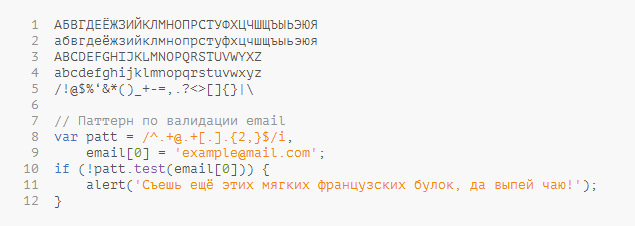
Более темное начертание
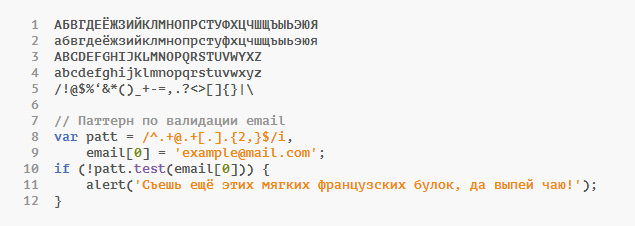
Droid Sans Mono
Семейство Droid разработано корпорацией добра для мобильных устройств. Доступен в Google Fonts, но эта версия имеет существенный недостаток — неперечеркнутый ноль. Версию с перечеркнутым, а также нулем с точкой, можно скачать на стороннем сайте.
Отличается довольно сносной кириллицей. Хорошо подходит для любого кода. Я уже несколько лет использую именно его. Но шрифт всё же имеет небольшие недостатки.
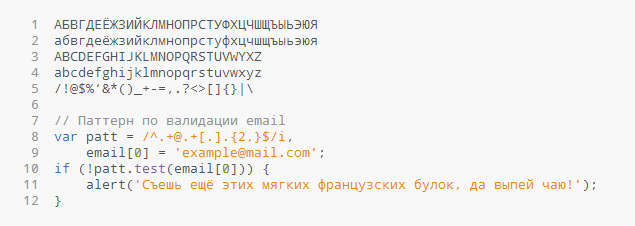
DejaVu Sans Mono
Обладает плохой кириллицей (но бывает и хуже). Не имеет ярких минусов в остальном. Но и выделиться тоже нечем.
Cousine
Шрифт от автора Droid Sans, созданный для разработчиков. Можно скачать с Google Fonts.
Кириллица на уровне DejaVu. Остальное симпатичное и читабельное.
Нормальное начертание
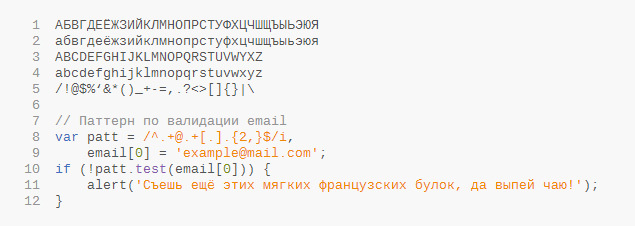
Более темное начертание
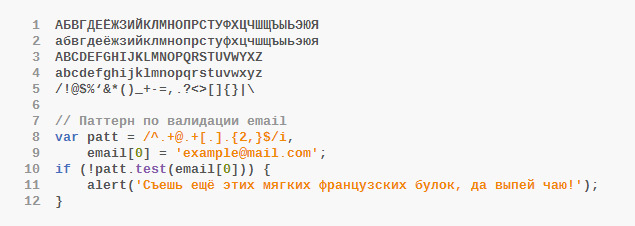
Ubuntu Mono
Входит в линейку фирменных шрифтов Ubuntu. Заявляется, что шрифты должны отвечать тону всего того, что делает Canonical.
Кириллица средняя. Для кода пригоден тоже средне. Может быть понравится любителям Ubuntu? Но стоит отметить, что шрифт весьма изящный.
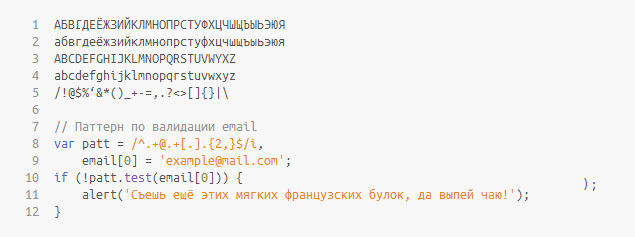
Fira Mono
Для использования в Firefox OS организация Mozilla разработала семейство шрифтов Fira. На Хабре есть обзор гарнитуры.
Кириллица на достаточно хорошем уровне, но не будет слишком сильно радовать глаз искушенного зрителя. Для кода подходит хорошо.
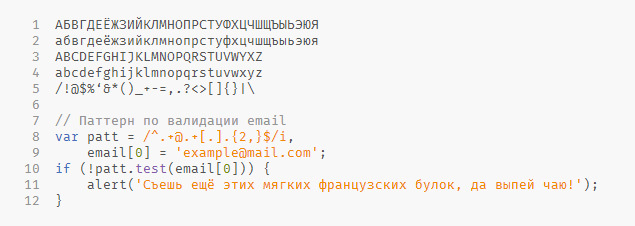
Inconsolata
Разработан специально для написания кода. По заявлению разработчика хорошо подходит как для экранов, так и для печати высокой плотности. Есть проект на Github, дополняющий гарнитуру кириллицей.
Выполнена кириллица на среднем уровне. Некоторые считают Inconsolata лучшим свободным шрифтом для кода, но я бы поспорил. Не нравятся глифы вертикальной черты и «собачки».